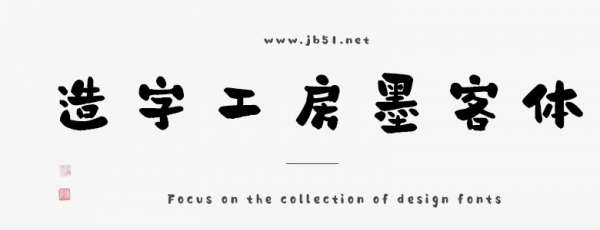
造字工房墨客體由上首造字字庫(kù)出品的字體,字體充滿淡泊之氣、尚樸之風(fēng)的全新手寫(xiě)字體。其用筆瀟灑,如文人墨客信步山川、悠游林泉的自在與灑脫。適合應(yīng)用于平面宣傳設(shè)計(jì)、網(wǎng)頁(yè)設(shè)計(jì),書(shū)法字帖等領(lǐng)域,需要的朋友可以前來(lái)本站下載。
造字工房墨客體是一款充滿淡泊之氣、尚樸之風(fēng)的全新手寫(xiě)字體。其用筆瀟灑,如文人墨客信步山川、悠游林泉的自在與灑脫;墨韻濃厚,彷佛文人墨客以筆為利器行俠仗義的豪情快哉。本字體為簡(jiǎn)體字庫(kù),采用OpenType/CID格式,Adobe-GB1-5編碼?;谥腥A人民共和國(guó)GB2312-80字符集標(biāo)準(zhǔn),另按需添加101個(gè)漢字。共收容字?jǐn)?shù)6864CJK漢字,ASCII常用字符100個(gè)。